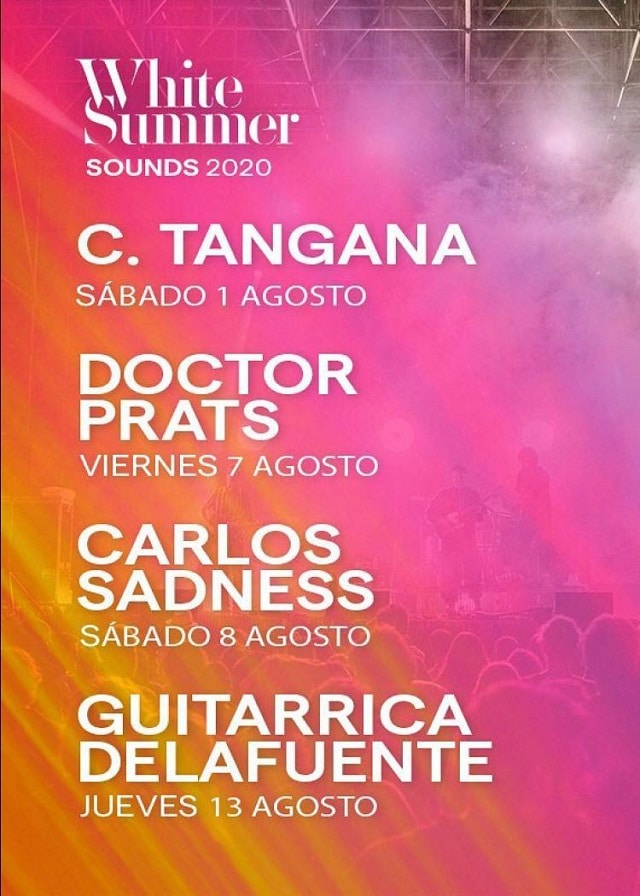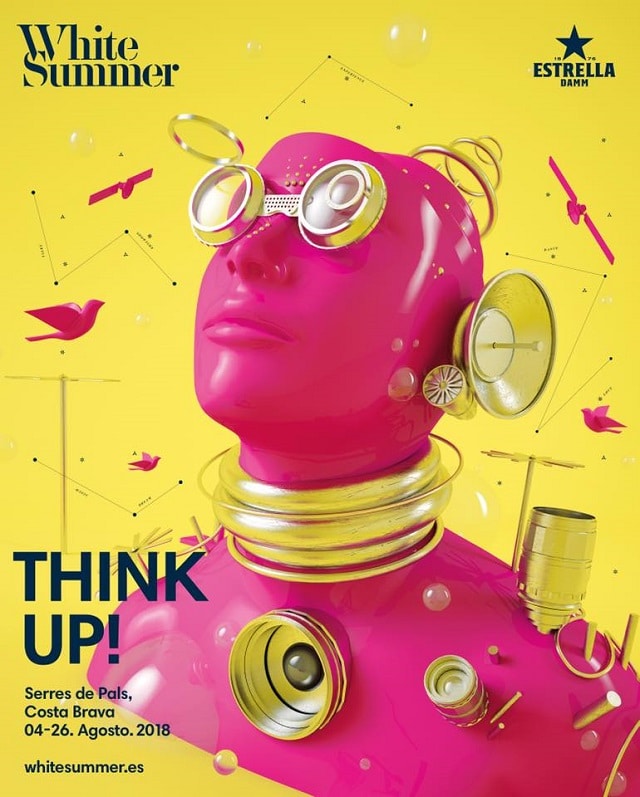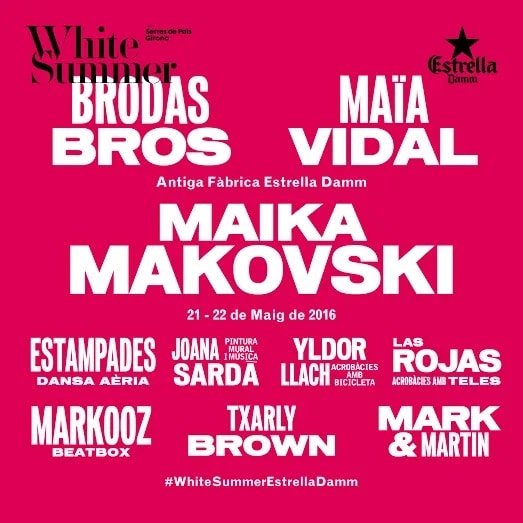
Como seguramente ya habréis leído en este blog, el lettering, en realidad, es la rotulación para letreros y para carteles. Si las letras para esta finalidad las dibujamos a mano, se llama hand lettering. Una vez aclarada estos términos, entenderéis la importancia de este artículo, ya que vamos a hablar de la finalidad principal del lettering y del hand-lettering: diseñar y dibujar letras para la rotulación. Hoy os vamos a hablar de los mejores tipos de letras para carteles, atendiendo a su diseño, a su legibilidad y a su capacidad para llamar la atención.
Tanto si vais a realizar un lettering a mano para luego vectorizarlo y pasarlo a digital para diseñar el cartel (ya sea de un evento tipo un concierto, para una película…), como si directamente vais a elegir una tipografía para diseñar el cartel y luego llevarlo a una imprenta online o física, estad muy atentos, porque esta información os va a interesar.
La legibilidad
A veces nos obnubilamos o nos cegamos con un tipo de letra del tipo Brush o una letra con formas caprichosas y muchos efectos que, si bien es cierto que llama la atención, en muchas ocasiones dificulta la lectura. Como diseñadores, estáis acostumbrados a leer ese tipo de letra, pero el público en general, no. Cuando diseñéis un cartel y dudéis del tipo de letra, enviádsela a un familiar o amigo que no esté familiarizado con el mundo del diseño y del lettering para hacer la prueba de si se lee bien o no. Por lo tanto, en el lettering para carteles, conviene escoger una letra con buena legibilidad, que se entienda al primer momento. Un ejemplo de ello es el cartel que vemos aquí arriba con unas letras mayúsculas sin remates o sin serifas, tipo Helvética Condensed, muy fáciles de leer y, al mismo tiempo, resultan atractivas. En este punto os queremos sugerior que, si tenéis que imprimir carteles, se pueden imprimir cómodamente en una imprenta online como ProPrintweb.com
El diseño
Siempre que hablemos de diseño, sea cual sea el ámbito, nos conviene fijarnos en la escuela Bauhaus, también en el diseño de los carteles de sus exhibiciones, así como en el tipo de letra que utilizan. Sus rotulaciones son funcionales, prácticas, es decir, cumplen con su cometido: que se lean a simple vista, pero sin descuidar el diseño, lo cual las hace más llamativas al ojo humano. Fijaos, si no, en el cartel que hemos escogido en el que anuncian su exhibición en la Weimar Gallery. Lo tiene todo: legibilidad, diseño atractivo de las letras, buena composición y unos colores primarios que llaman mucho la atención.
La composición
Como acabamos de ver en el cartel de la Buhaus, en la rotulación o lettering, la composición, es decir, la manera en la que se reparten las letras en el espacio es muy importante para comunicar bien el mensaje:
- Lo primero es elegir las palabras que queremos que destaquen y que vayan en mayor tamaño.
- Lo segundo, escoger una forma general o silueta en la que se enmarquen las palabra.
- Lo tercero, rellenar esa forma o silueta con rectángulos en los que va a ir cada palabra.
- Lo cuarto y último, si es necesario, rellenar los espacios que las palabras no puedan abarcar con otras formas simples.
En el cartel que hemos escogido de ejemplo, se ha determinado que la palabra importante y a destacar sea «Originals«, por eso va en mayor tamaño que el resto. En lo segundo, se ha escogido una forma, a grandes rasgos, rectangular, que se ha rellenado con palabras y con la forma sencilla de un coche para cumplir mejor con la forma elegida. Es una buena composición.
Los colores
Por último, en el lettering para carteles son importantes los colores, que tienen que ser llamativos, pero adecuados al diseño y a la imagen de lo que queremos transmitir. Generalmente, los colores primarios RGB como el rojo, el verde y el azul son idóneos para los carteles, así como los CYMK, es decir, el cian, el amarillo, el magenta y el negro. Por supuesto, el blanco funciona muy bien en los diseños en negativo. Si justamente estos colores mencionados no se adecuan a la imagen de marca para quien estamos realizando el cartel, entonces, hay que escoger unos colores parecidos a esos, pero con matices de tonos, y que combinen bien entre ellos.
Fijaos, en general, cómo casi todos los carteles del festival White Summer que hemos puesto arriba utilizan estos colores, en especial el magenta y el amarillo combinado con letras blancas o negras legibles. Son muy llamativos y eficaces, así como que las letras tienen buena legibilidad.
Esperamos que estos consejos sobre qué lettering para carteles escoger os hayan servido de ayuda y que, al diseñar un rótulo, un cartel, la portada de un disco o cualquier comunicación visual tengáis en cuenta el tipo de letra y su legibilidad, el diseño de las letras, la composición de las letras y otros elementos y los colores.